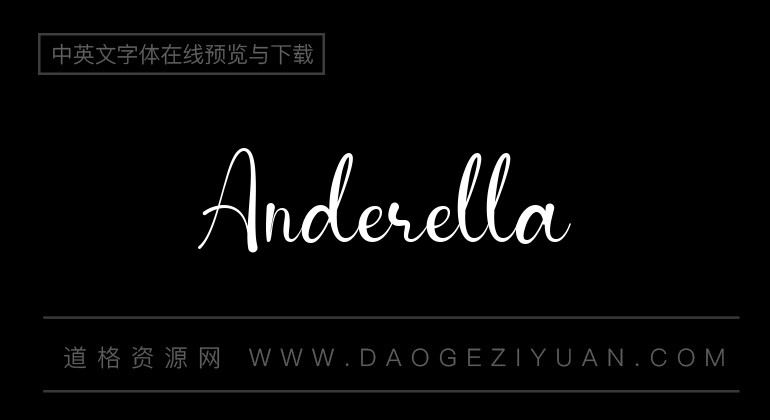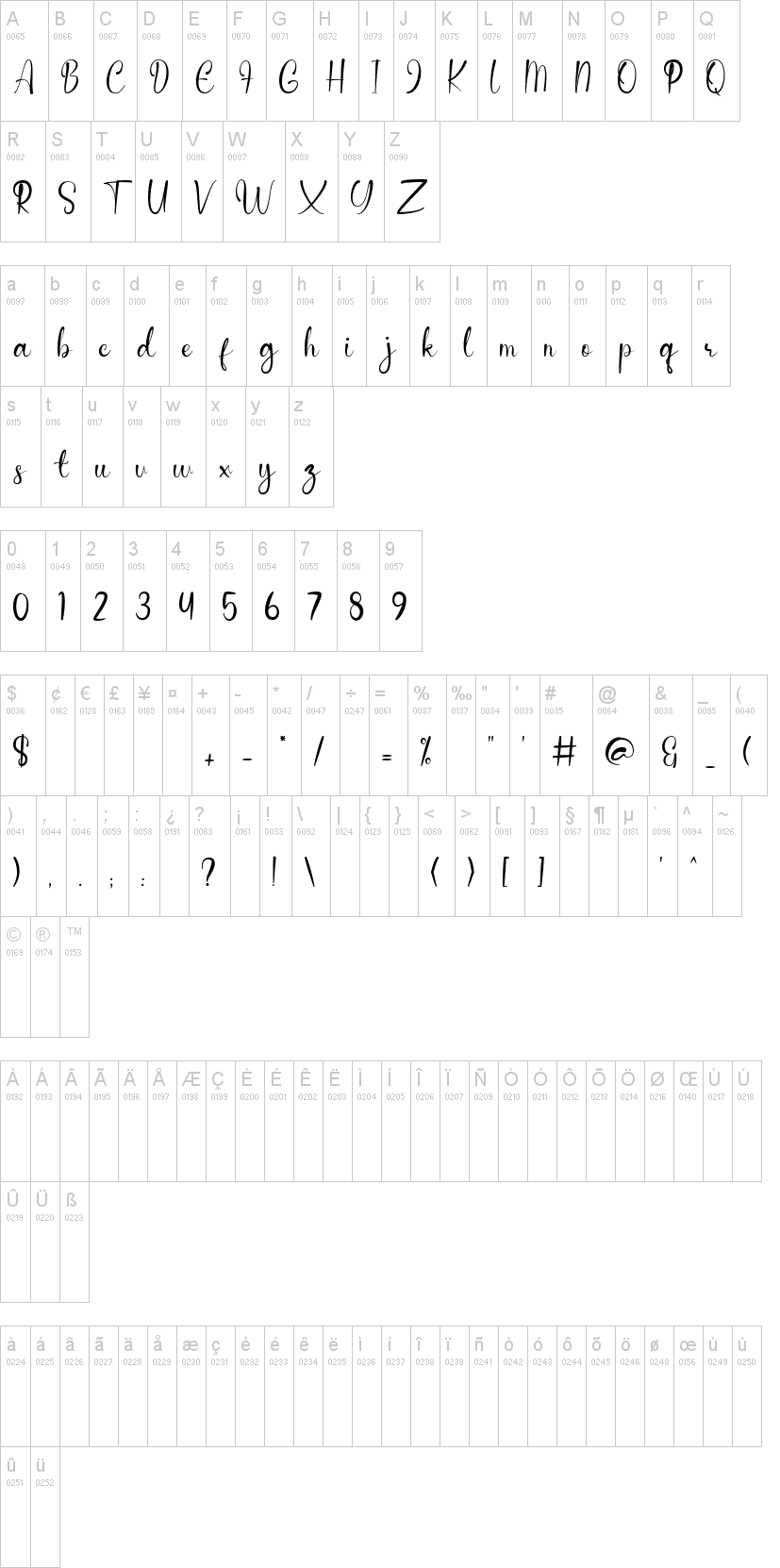
Anderella 字体是一款简洁明快的英文字体,它的特点是字体的线条细腻,字母比较大,笔画流畅,使用它可以让文字显得更加精致大方。Anderella 字体是一款简单易读的字体,它可以用于报纸、杂志、书籍、海报、广告、网页等等,它可以帮助你让文字看起来更加精致大方。内容介绍
Anderella是一款非常不错的手写艺术字体,具有很好的视觉感,适合于文化类的宣传设计、商业类品牌的广告和产品包装设计以及个性化文字排版等较多场景。